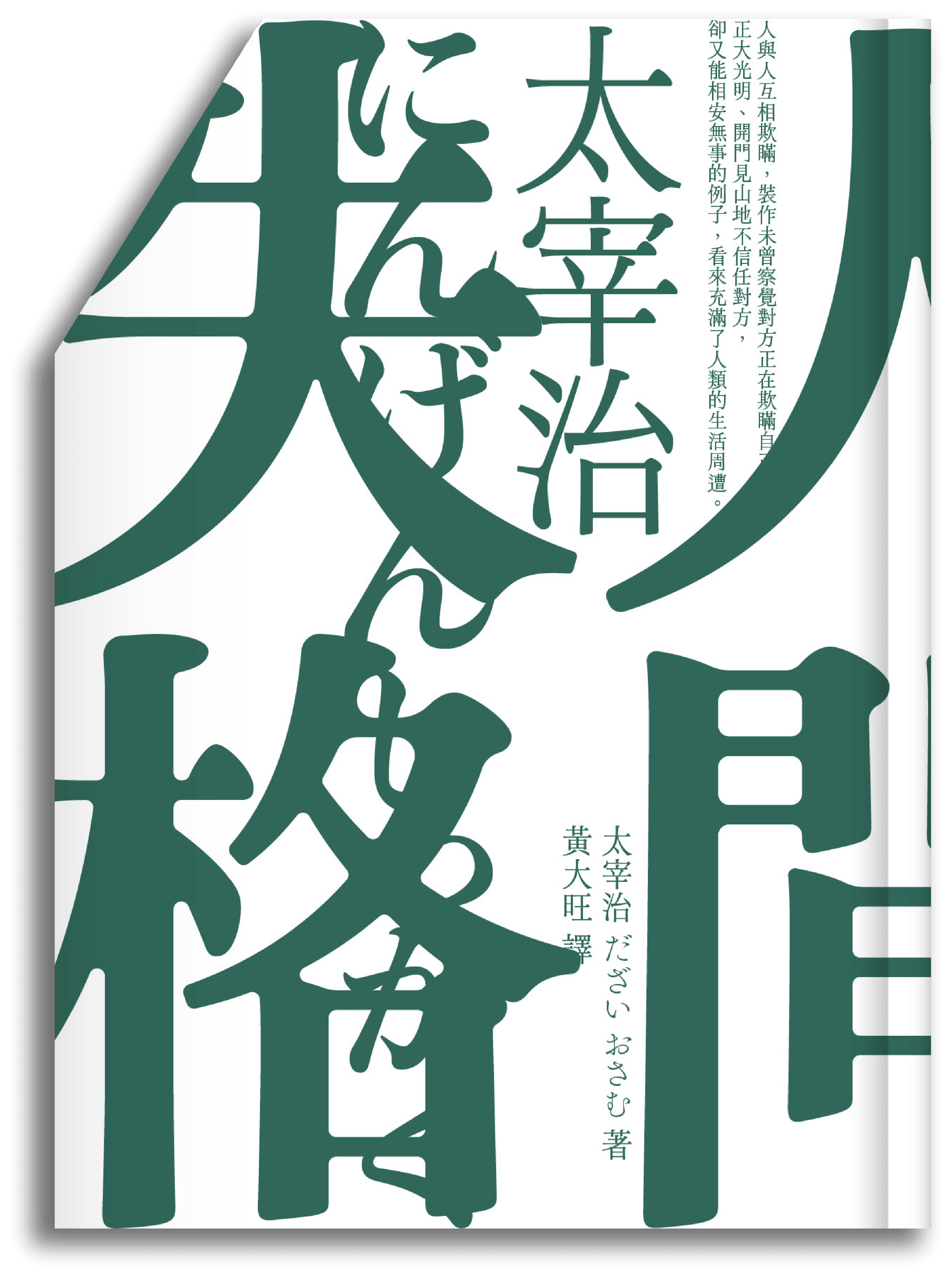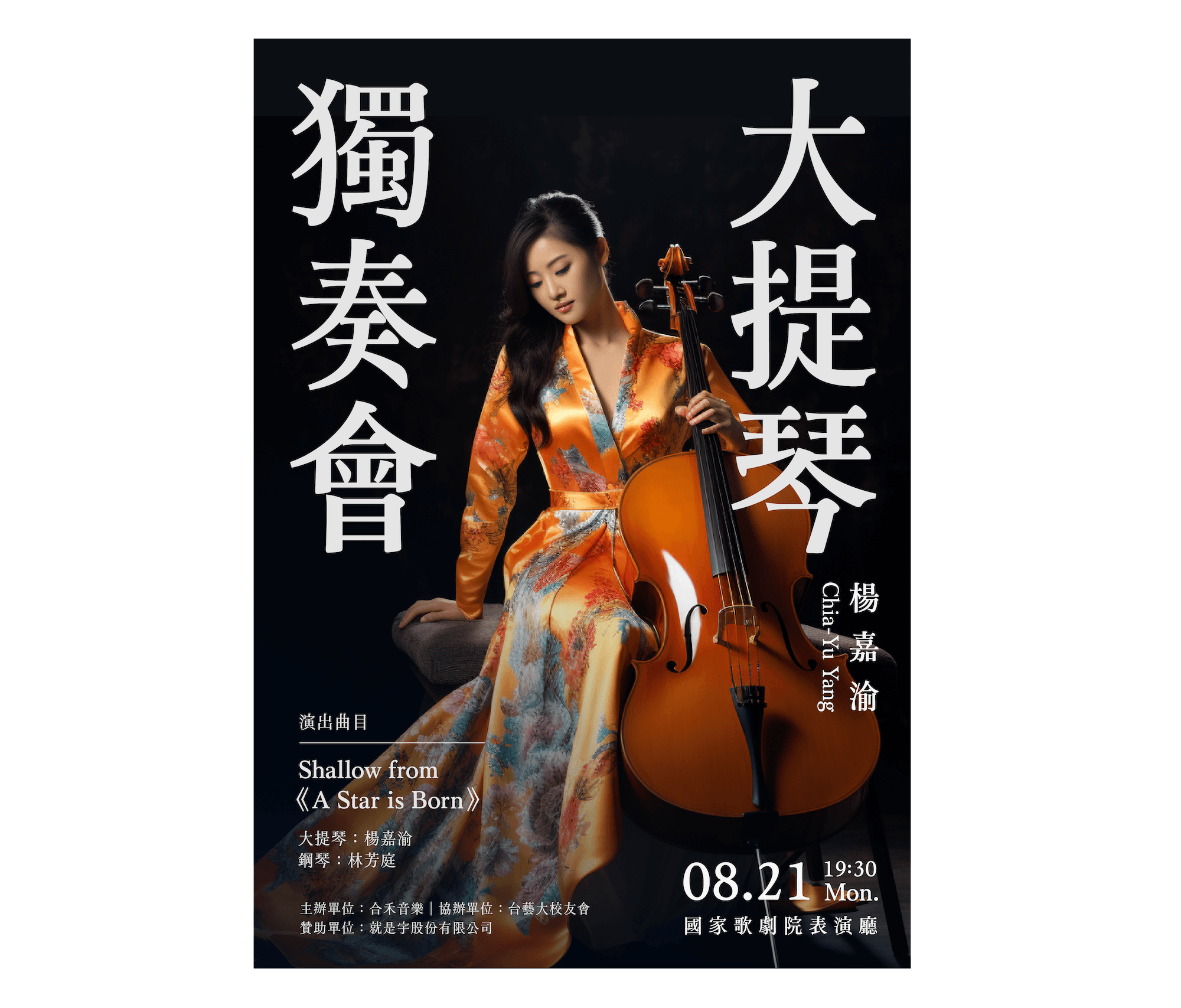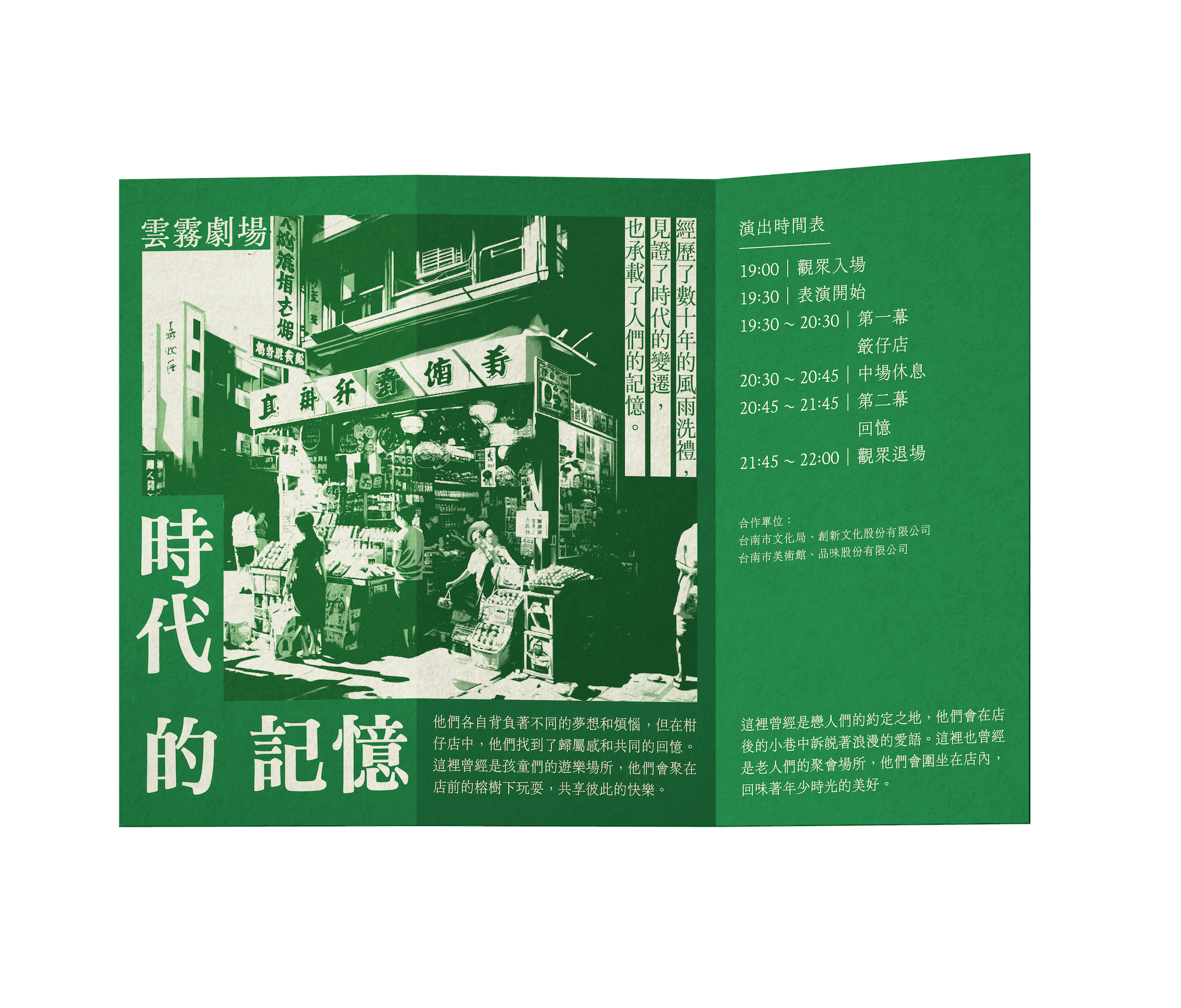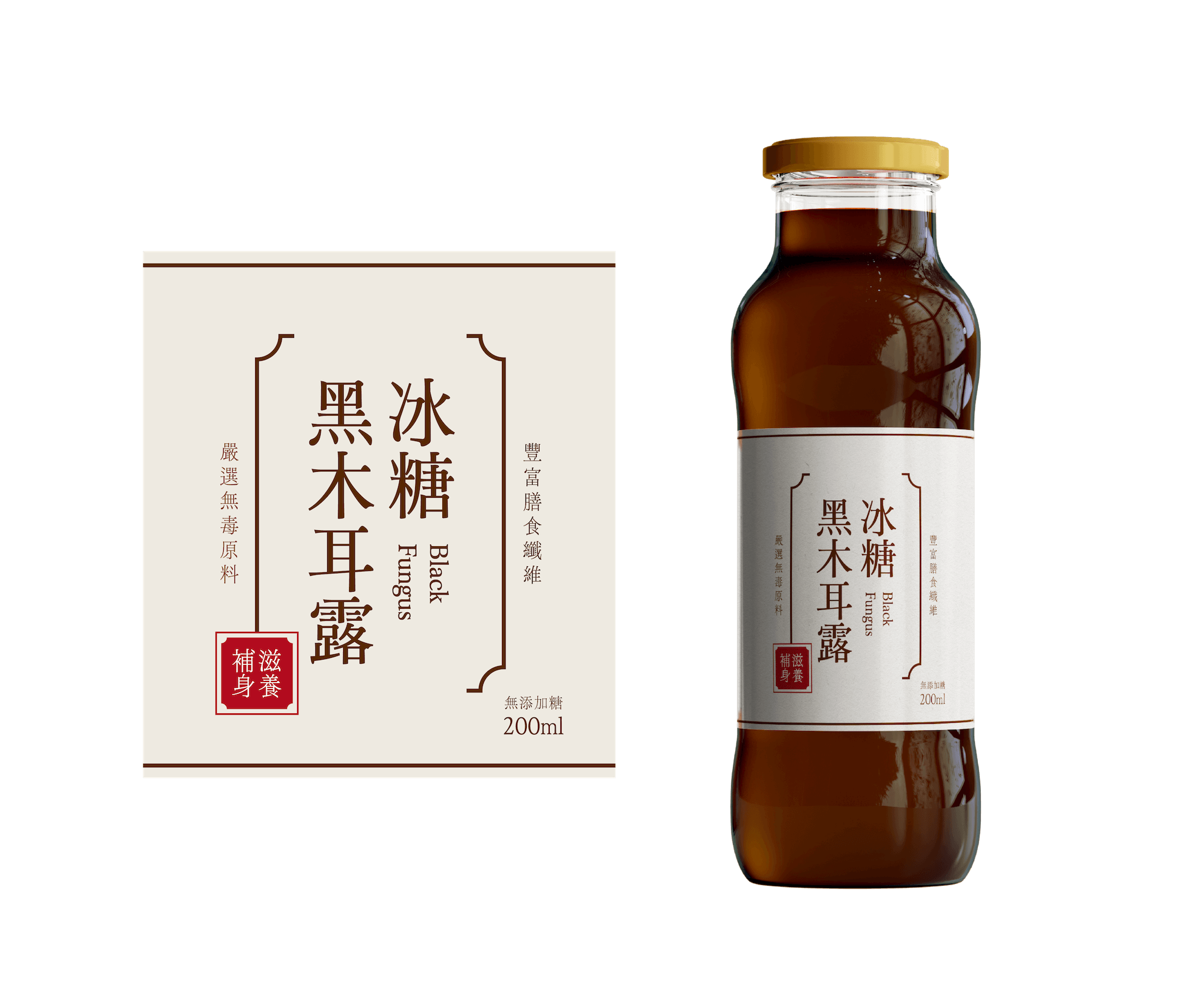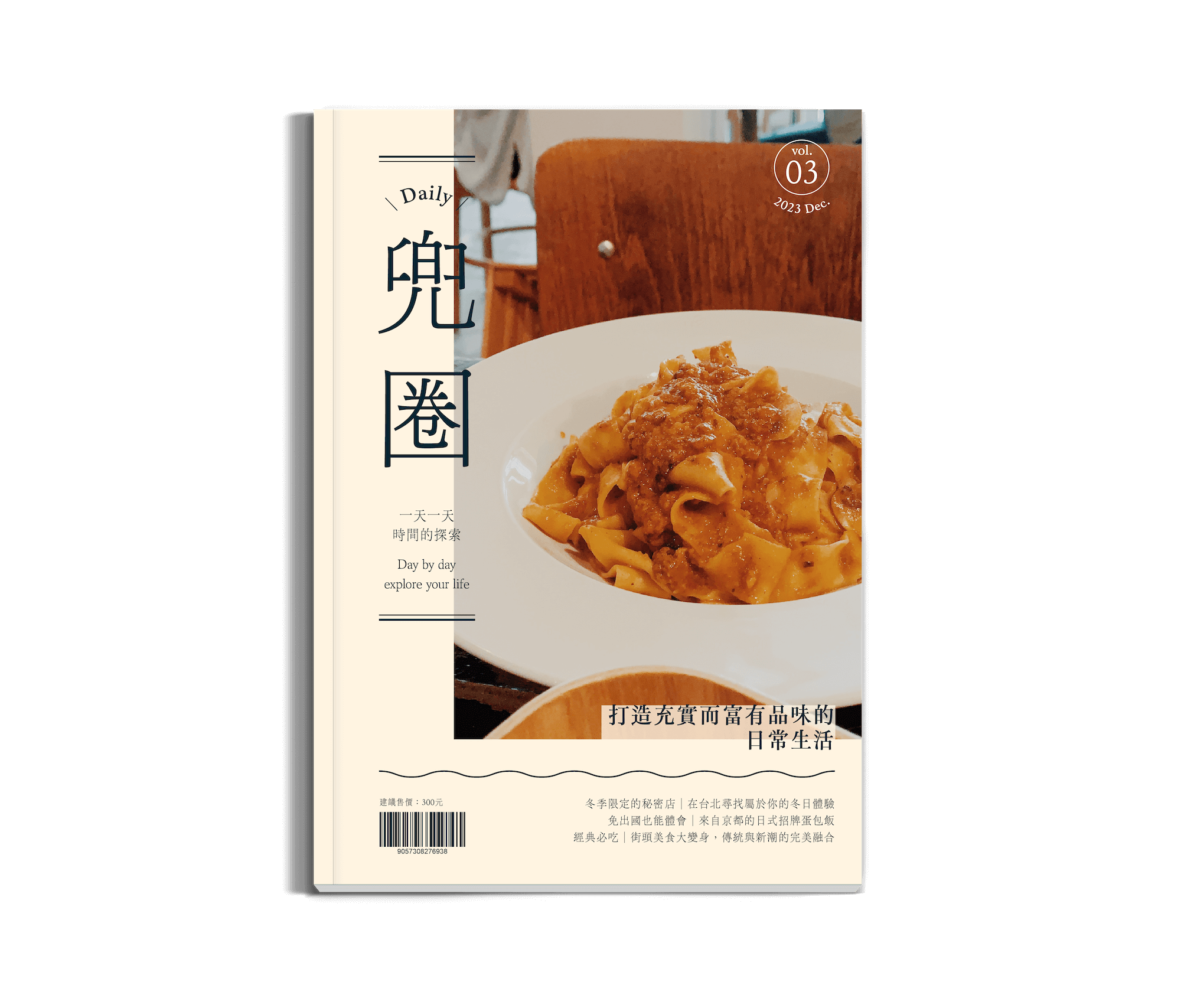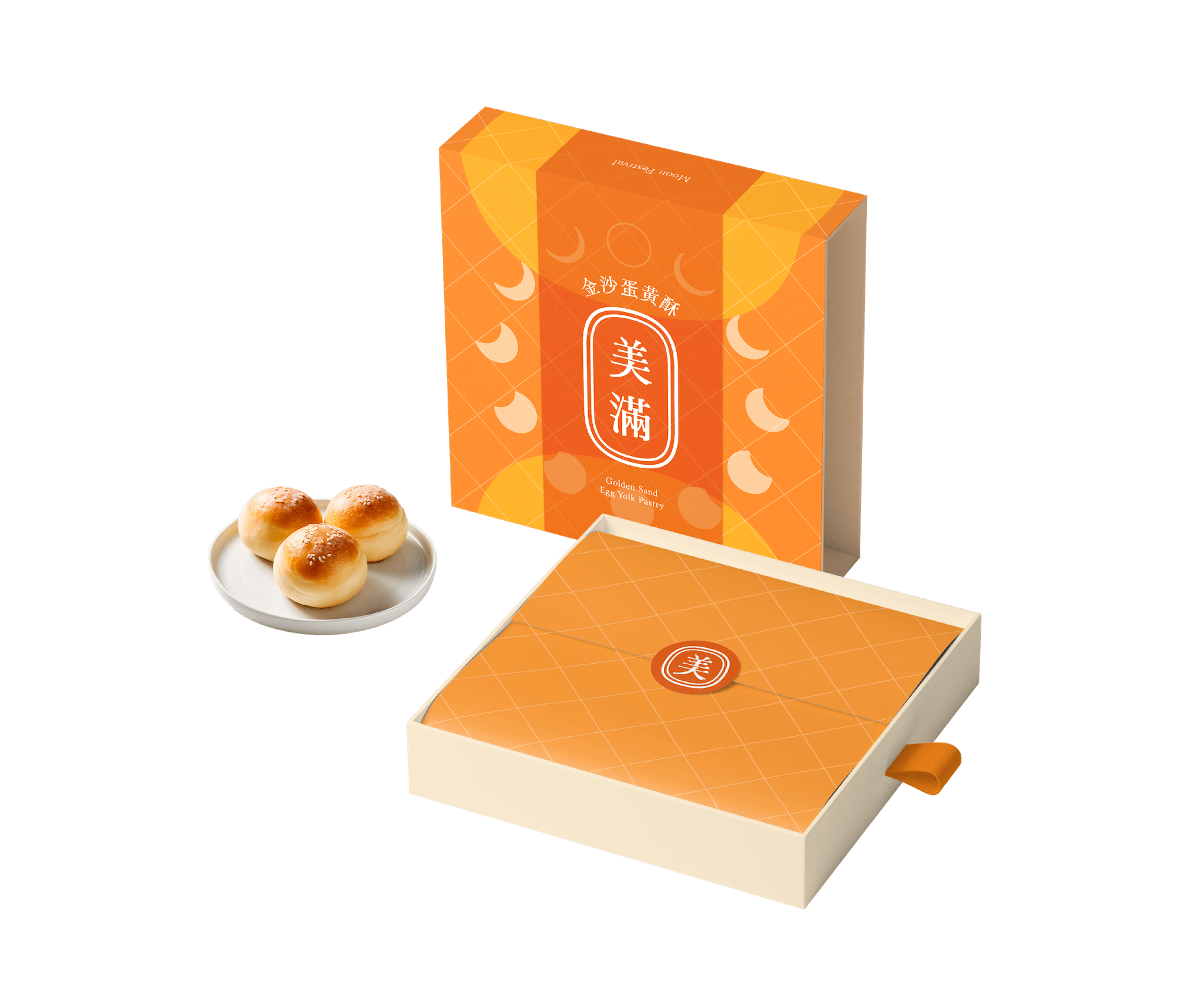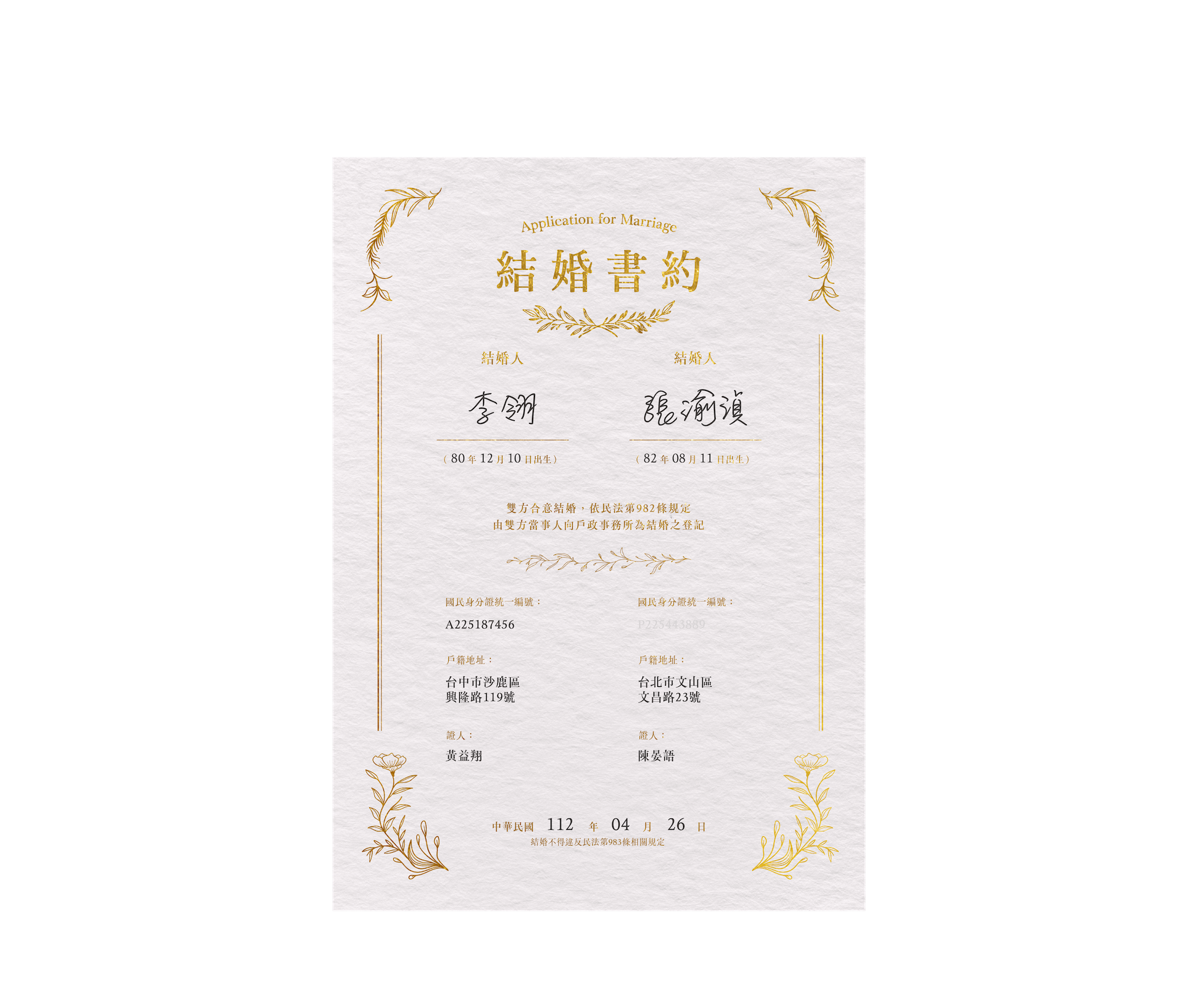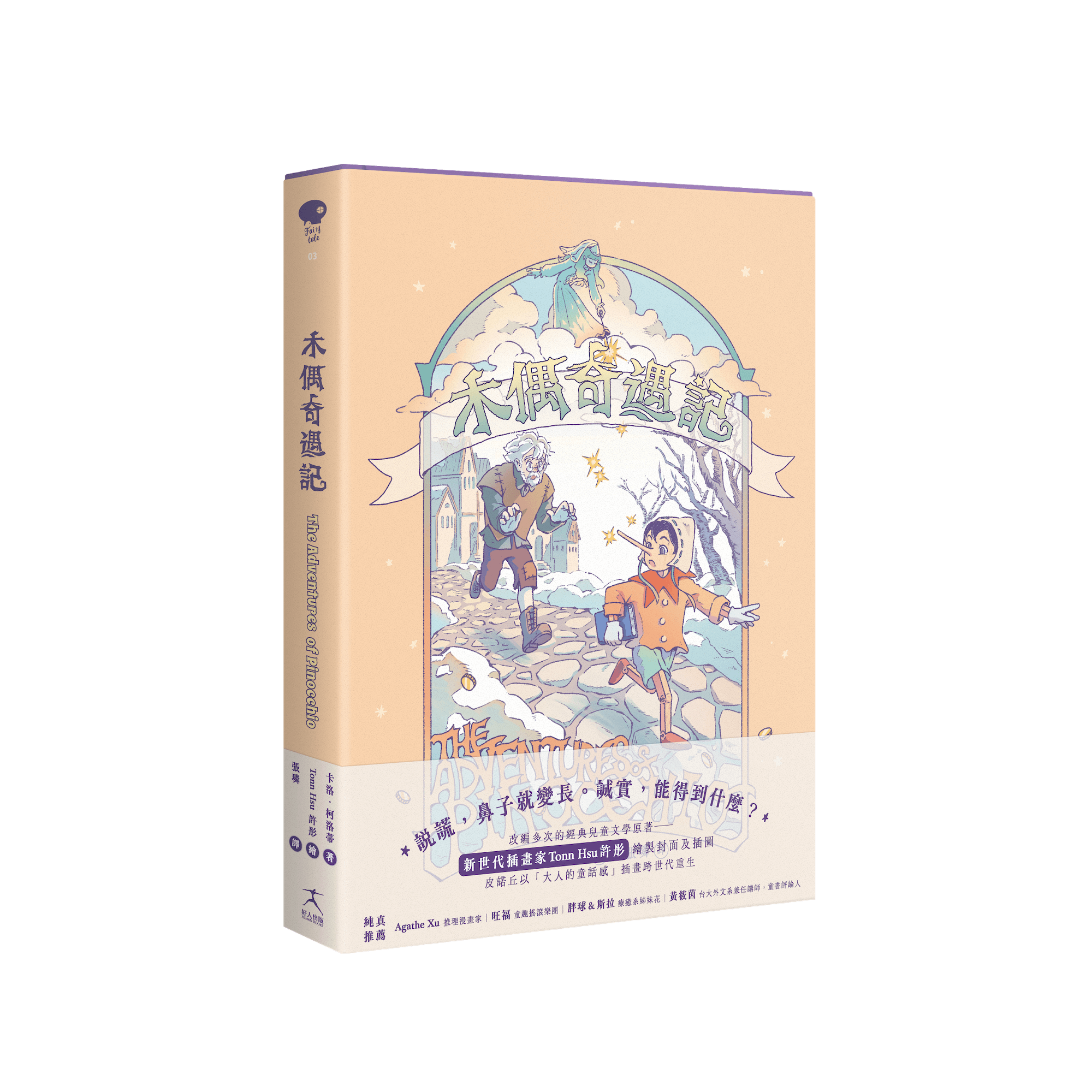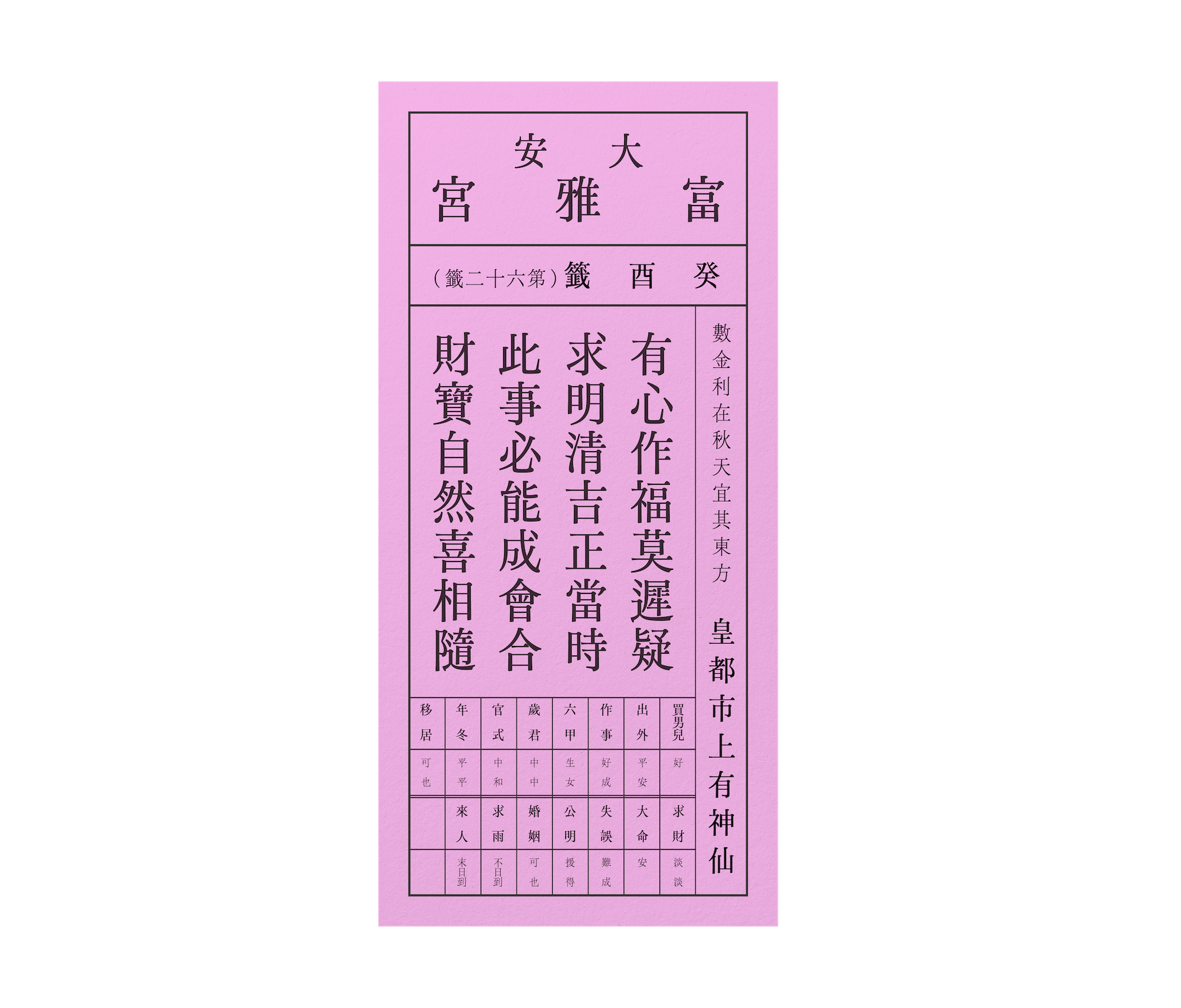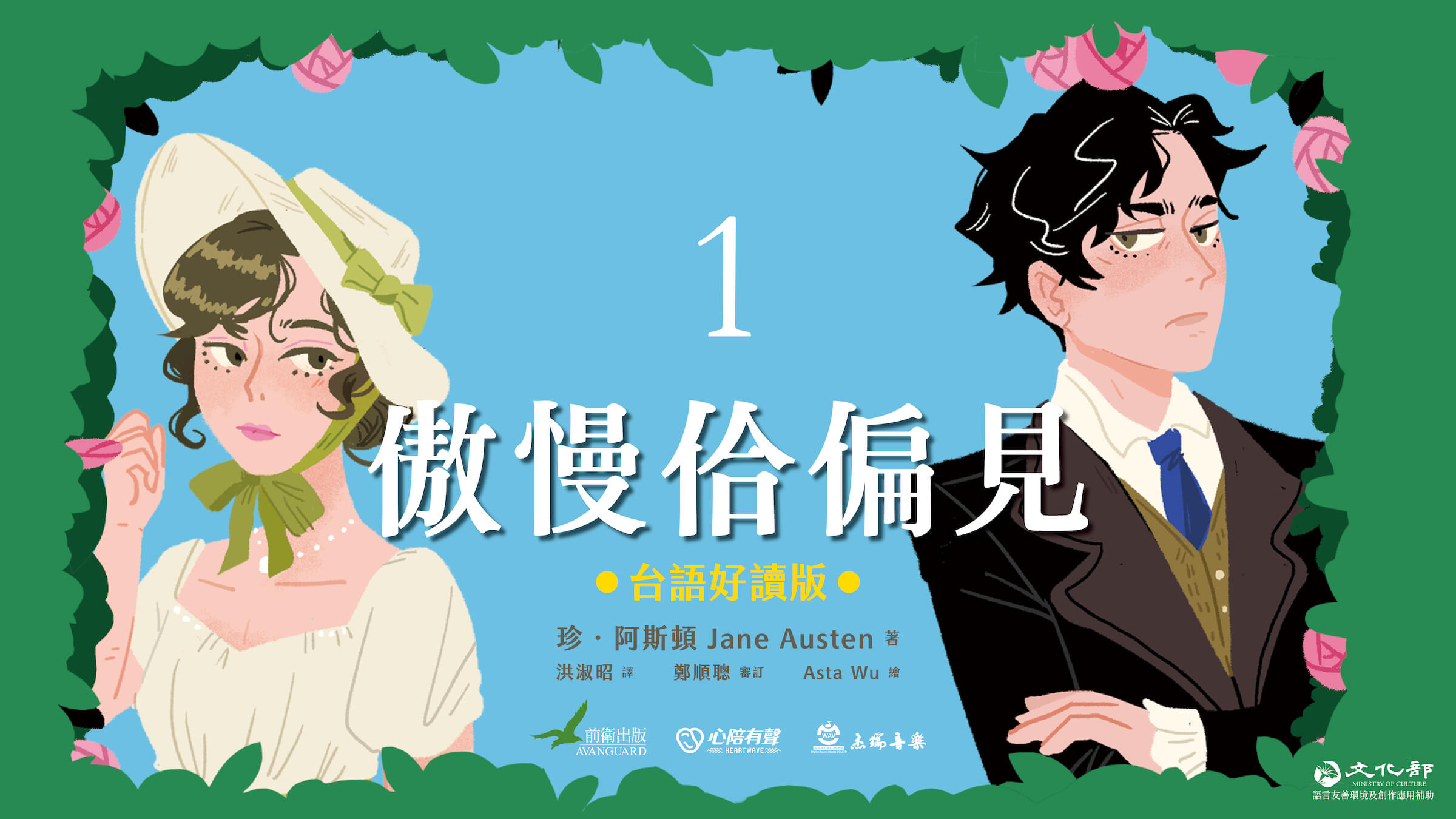
蘭陽明體
書寫如詩字體
一般明體
書寫如詩字體
蘭陽明體
突破典型框架,細膩描繪筆畫。走出數位化的設計限制,讓你創造更豐富的情感表達。
展讀蘭陽,
他們說
蘭陽明體值得買嗎?2021 年搶先贊助的他們,在各行各業中實地使用後,真心推薦。
最近用蘭陽明體印了篇幅一萬字左右的印刷物,因為在展示網頁上看到的範例都是新詩或,原本擔心排長文會有點厚重,不過效果非常好 ! 特別喜歡略為瘦長的輪廓和橫豎筆畫的粗細差異,雅緻又細膩,謝謝你們開發這麼好看實用的字體,也期待未來推出其他字重。
因為工作性質的關係,目前主要都是使用在書籍作品上。最近負責好人出版的「木偶奇遇記」設計編排,也用了蘭陽明體作為書名標準字以外的中文搭配字體,有兩種字重 & 兼具情懷與現代感的風格在書上真的很實用!(近日已出版XD 可以在書店看到了)也謝謝霞姐和 justfont 製作了這麼多超棒的字體!
很感恩這個創作,讓我有機會用台灣自製的美麗字體在電子閱讀器上閱讀心愛的作品。也期待未來的創作或 App 裡有機會加入這個字型的使用。
真的好喜歡用途非常廣泛的蘭陽明體,放在許多的設計上,看起來就是那麼的剛剛好,富有特色但不特別高調。是一款非常實用、非常好用的字體!
因為工作性質偏向編排公家機關內文,蘭陽明體的特色就是簡潔明瞭,做得很漂亮,閱讀上也比較輕鬆,希望可以多製作相關的字型。
明體從雕版而生,由楷書蛻變而來,是漢字閱讀的基本字體。它的故事裡,有書寫的情感,詩意的懷想。
書寫的情感,
詩意的懷想
以雕版氛圍,重新想像現代明體,嘗試改變文字方正的既定印象。助你創造更婉約溫柔的排版樣貌。
明體從雕版而生,由楷書蛻變而來,是漢字閱讀的基本字體。它的故事裡,有書寫的情感,詩意的懷想。以雕版氛圍,重新想像現代明體,嘗試改變文字方正的既定印象。助你創造更婉約溫柔的排版樣貌。
浪漫懷想
讀月
採古法,跳脫正方格局,回歸漢字原始形狀。
給人典雅第一印象,興起浪漫懷想。
人的情感
淺水
不隱藏手的姿態與人的情感。
婉轉流動的細節,可以細細欣賞。
典雅雋永
蘭陽
調和剛與柔,層次豐富。
放大看、當內文,都禁得起反覆品味。
你的流域裡,
豐富地貌已浮現
合作無間的字型家族,用於內文、標題、各式呈現為設計搭配帶來豐富層次。
• W2
內文、標題,多用途
我們不都是虛度昨日
以達明日之人嗎
不都是惶惶提起衣襬
立於臨水之淵者嗎
• W3
用於內文,優雅細膩
• W4
稍粗內文,適螢幕
• W5
副標題用,更有層次
• W6
用於標題,厚重古雅
• W7
主標題用,典雅大器
用心描繪跨越時空,不分國界。除了風格相稱的歐文、數字,更支援台羅拼音,持續傳遞本土語言之美。
字是恆久的風景,長過寫字的人。這份溫柔的作品,交給你灌溉更多美麗的事物。
不只美,更好用。除了漢字與歐文,標點、注音、數字、符號的和諧搭配在此細細體會
從我的故事,
流到你的故事
溝渠、湧泉、綿綿細雨、蘭陽溪⋯⋯水的意象啟發字的創作。以故鄉之名,點亮字的精神,稱為「蘭陽明體」
「 現代數位感的創作已經達到巔峰了。
到了這個階段,我想做更有感情的作品。 」
林霞
林霞,台灣宜蘭人,justfont 字型總監。三十餘年設計經驗,催生「金萱」、「金萱那提」字型系列,並在「凝書體」、「激燃體」與「台灣道路體」創作過程中擔任總顧問。
• 巧合
蘭陽明體的架構脫胎於民初雕版印刷《澗于集》。林霞團隊鑽研年餘,才發現作者竟是張愛玲的祖父⋯⋯
• 非典型創作
與文訊出版社合作,在公車捷運詩文上,蘭陽明體曾以「未知字體」的低調姿態出現在台北生活圈中⋯⋯
• 宜蘭的水
地名取字名,有理。但這麼多地方,怎麼選?想了想,才發現人生許多問題的解答,往往在自己身邊⋯⋯
突破既有框架,並非易事。除了持續不懈嘗試,更需要勇氣。長達三年前置開發中,設計團隊累積了許多心得,希望與你分享